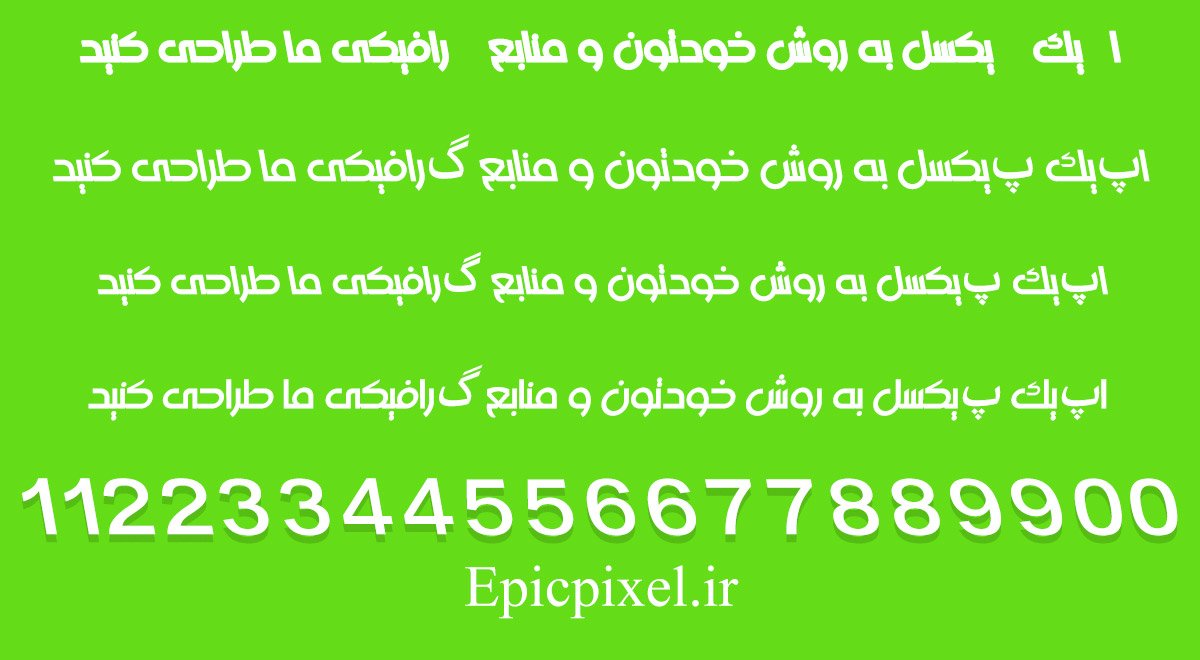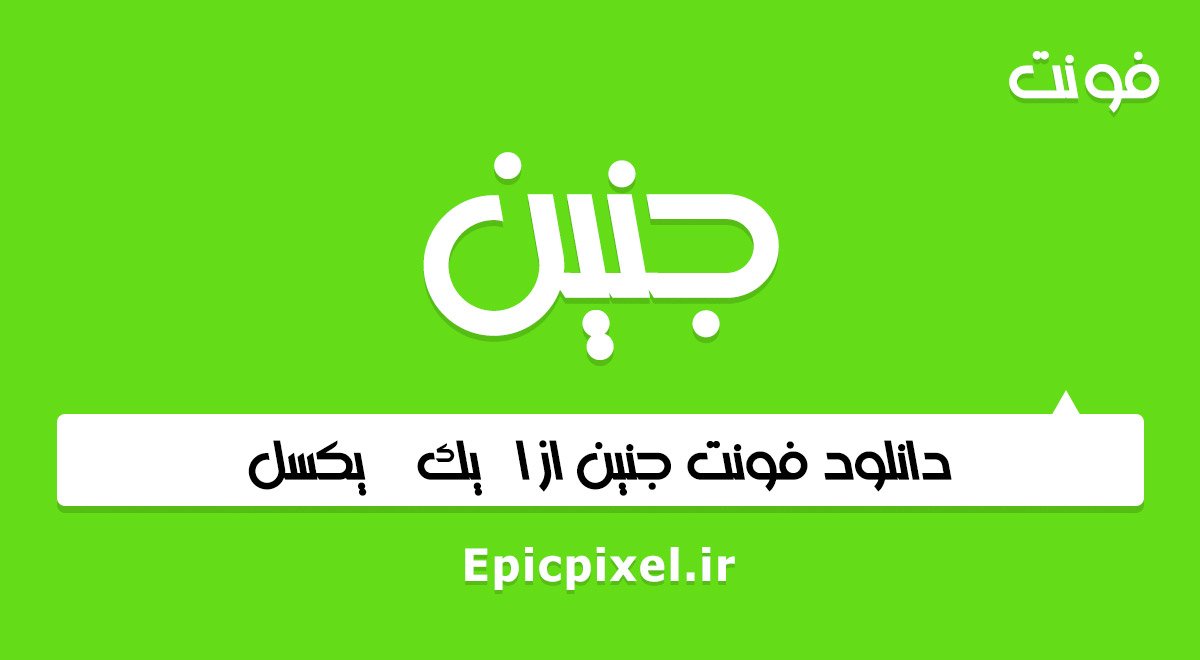
فونت جنین عربی، با طراحی خاص و منحصربه فرد خود، جلوه ای زیبا و چشم نواز به نوشته های شما می بخشد و به خصوص برای طراحی هایی با حال و هوای سنتی و مذهبی، انتخابی ایده آل است. این فونت با ظرافت و دقتی که در طراحی حروف آن به کار رفته، خوانایی بالایی را در اندازه های مختلف ارائه می دهد و در عین حال، زیبایی خاص خود را حفظ می کند.
اگر به دنبال فونتی هستید که هم در طراحی های چاپی مانند پوسترها و جلد کتاب ها و هم در طراحی های دیجیتال مانند وب سایت ها و شبکه های اجتماعی، جلوه ای متفاوت و جذاب ایجاد کند، فونت جنین عربی گزینه ای بی نظیر است. این فونت به دلیل طراحی حرفه ای و وزن مناسب حروف، در انواع پروژه ها از طراحی لوگو گرفته تا تایپ متون طولانی، به خوبی عمل می کند و به کار شما ارزش افزوده می بخشد.
یک فونت خیلی خاص و گرد و قلمبه هست